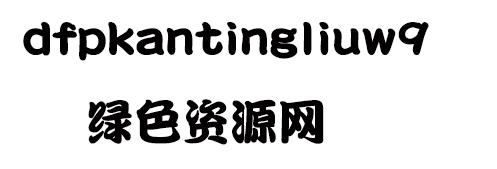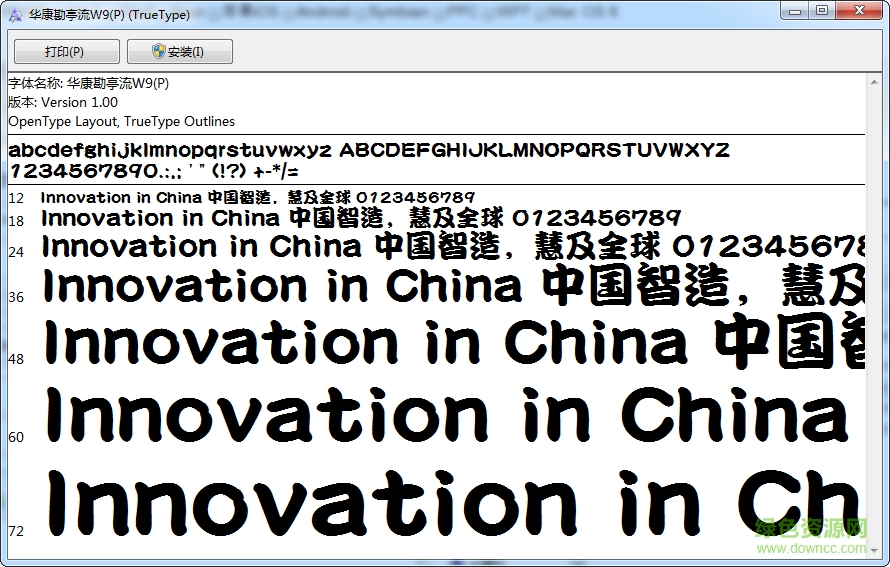
dfpkantingliuw9是什么字體?dfpkantingliuw9就是華康勘亭流w9 p普通字體,該字體多見于日式風(fēng)格的廣告上,圓潤親切,用在包裝設(shè)計和招聘設(shè)計方面效果非常好,需要的朋友們快來本站免費(fèi)下載吧!
勘亭流體是一種江戶時代(大體相當(dāng)于我國明末清初那段時間)所使用的廣告字體。由戲劇界人物岡崎屋勘六設(shè)計,勘亭流就是得名自其別號“勘亭”。